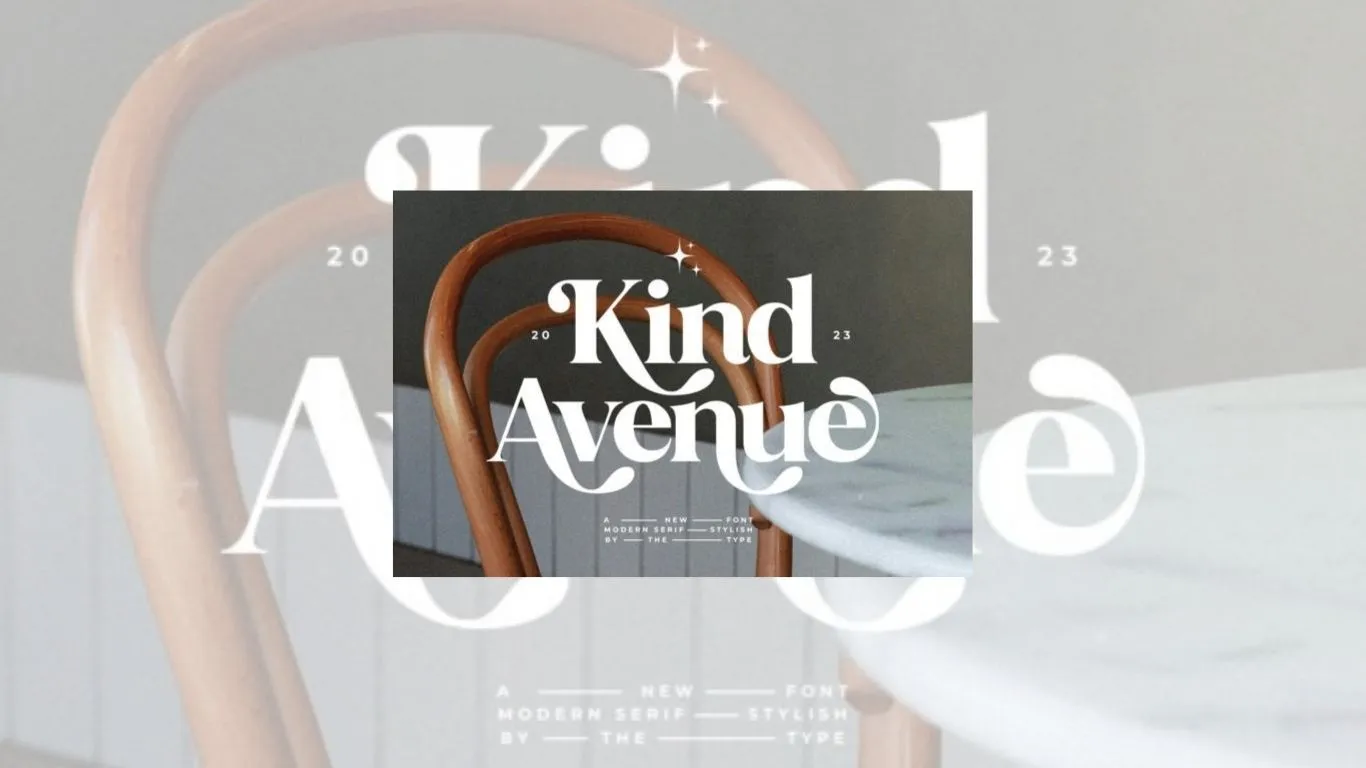
喜歡復古風設計的朋友,今天有好消息啦!Creative Fabrica 今日限時免費送出字體 Kind Avenue,帶有時尚感的復古 Serif 字型,原售價為 $12 美元。它的特色在於能靈活切換保守的傳統 Serif 風格,或加入花式替代字符 (Alternates) 與連字 (Ligatures) 打造更有個性的版面。免費下載還包含商業授權,可以放心用在個人或商業創作中,但記得,只有今天才免費啊!
Kind Avenue 是由設計師 The_Type 創作的復古風格 Serif 字體,原定售價 $12 美元,今日限時免費下載 。
1. 雙重個性:可作為保守沉穩的傳統 Serif 字型使用,同樣能透過替代字符 (Alternates) 和連字 (Ligatures) 呈現現代感。